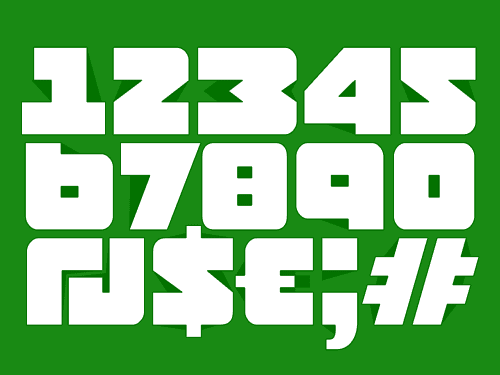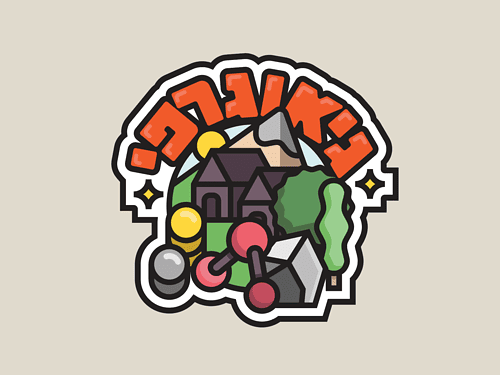
פונט דו־לשוני, גמיש, ריבועי וכבד המושפע מטיפוגרפיה עברית מהשנים המוקדמות של ישראל
האותיות מתאפיינות במראה בלוקי ויציב במיוחד, והן מגיעות בחמישה רוחבים (משקלים), בהם ניתן להשתמש בנפרד או לשלב אותן יחד וכך להגמיש בצורה אופקית את המלים הנוצרות מהם.
בשנת 2018 נוספו לקרוואן אותיות Uppercase באנגלית וגרסא פרמטרית!